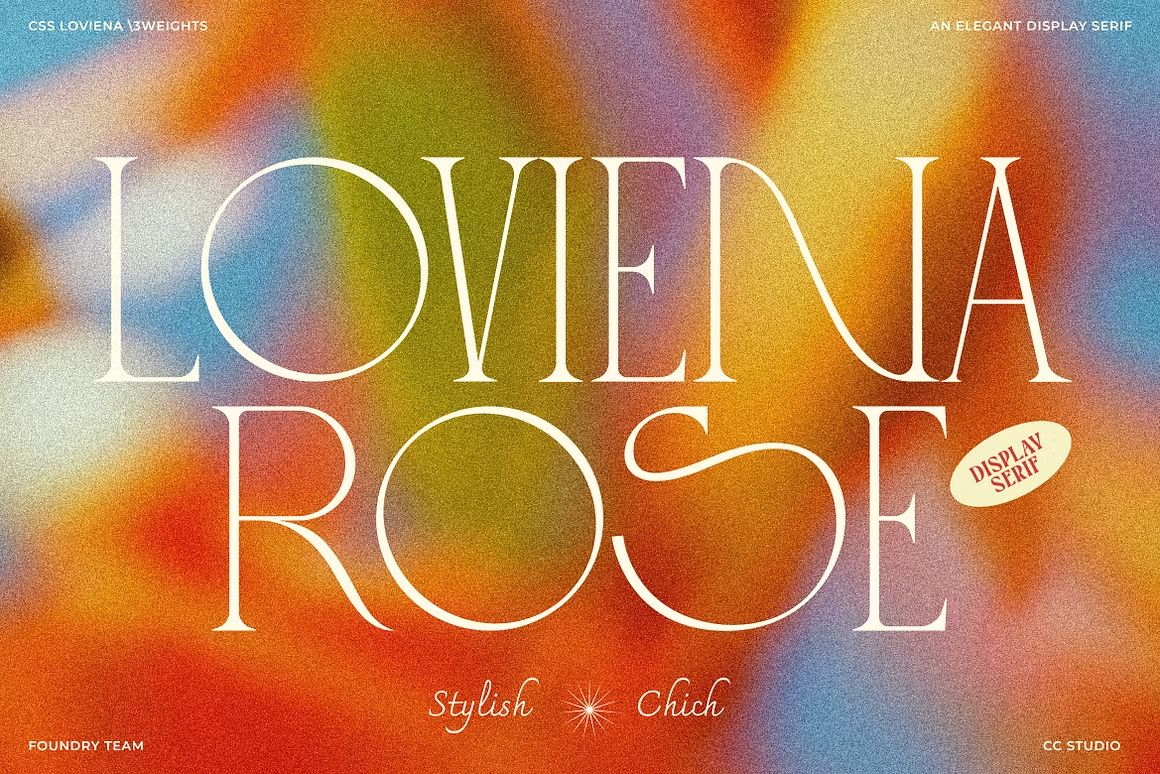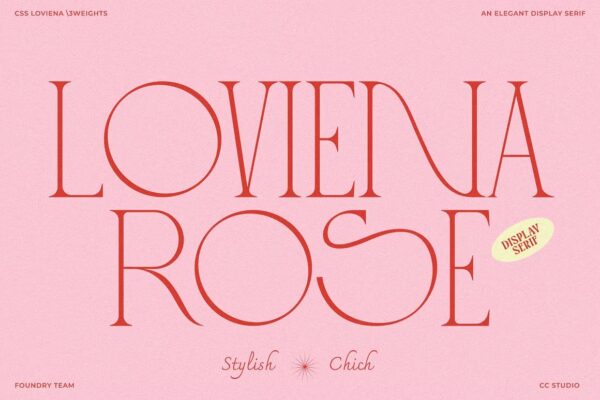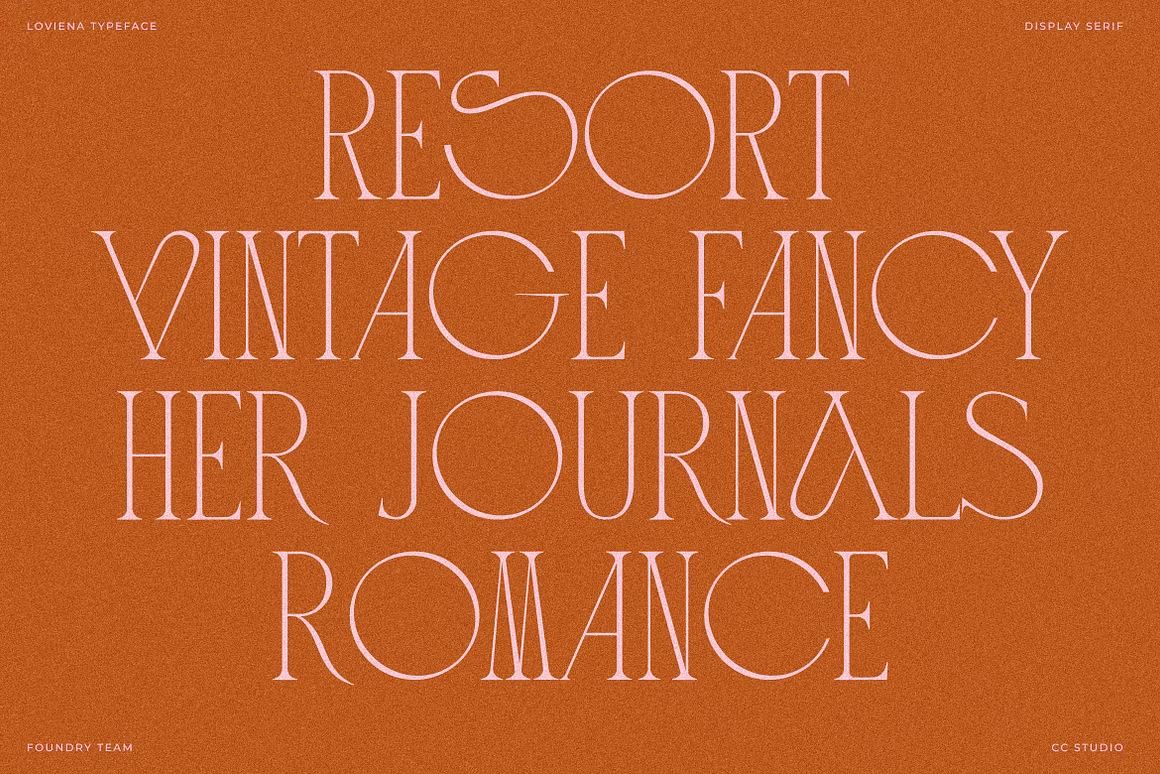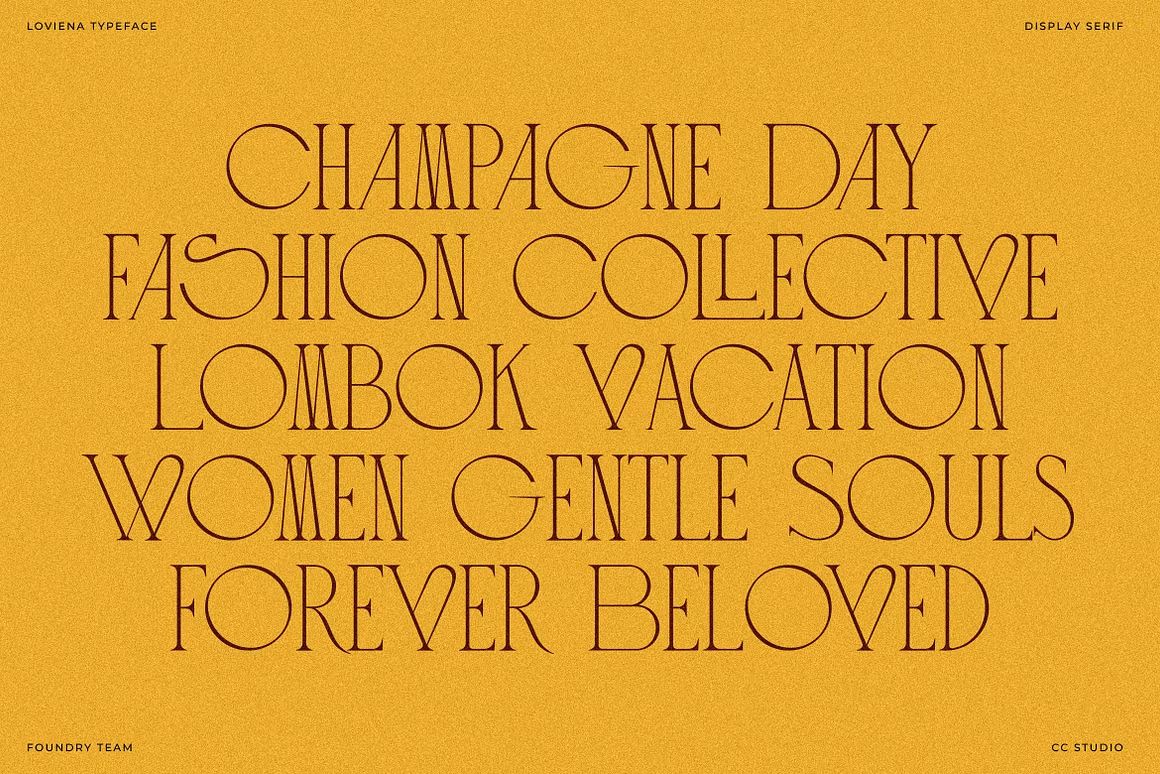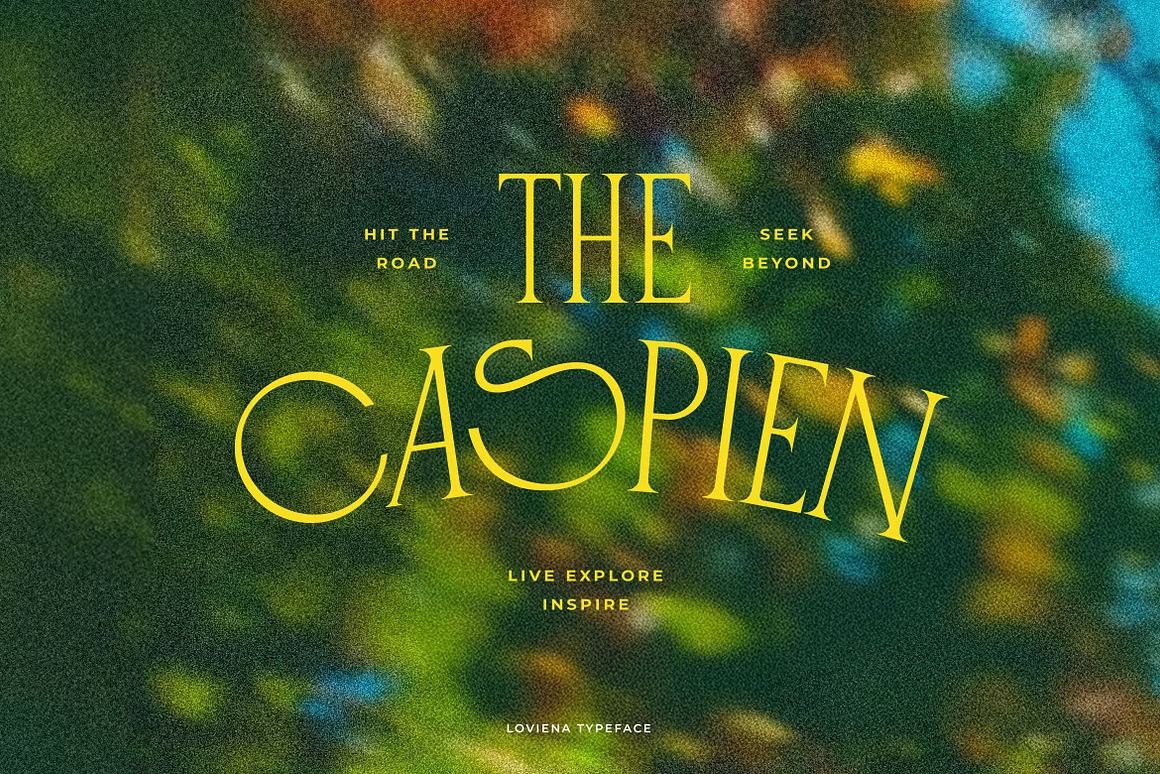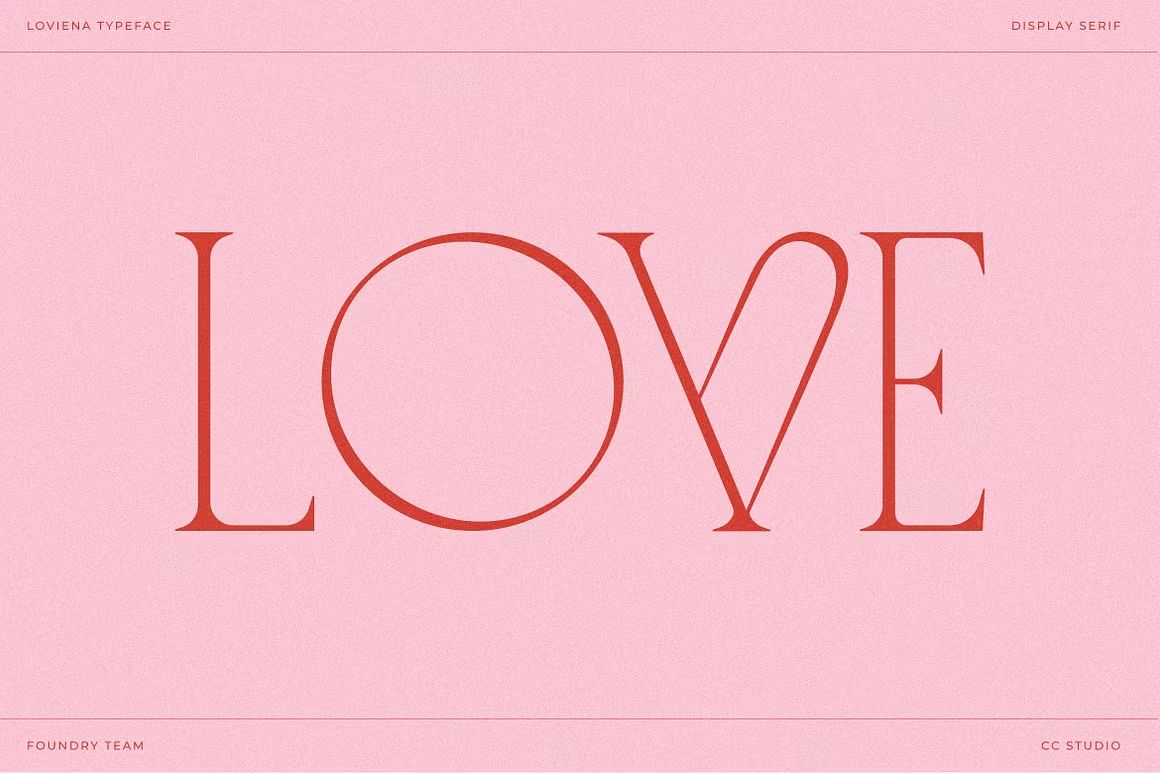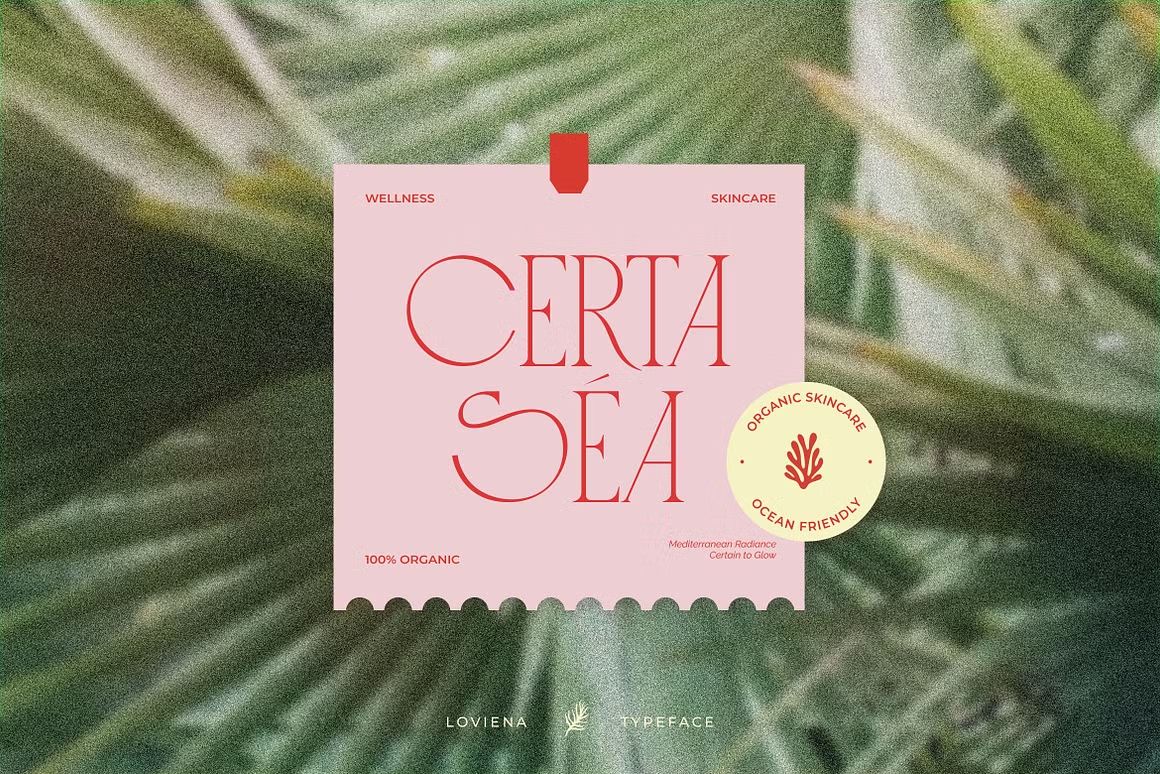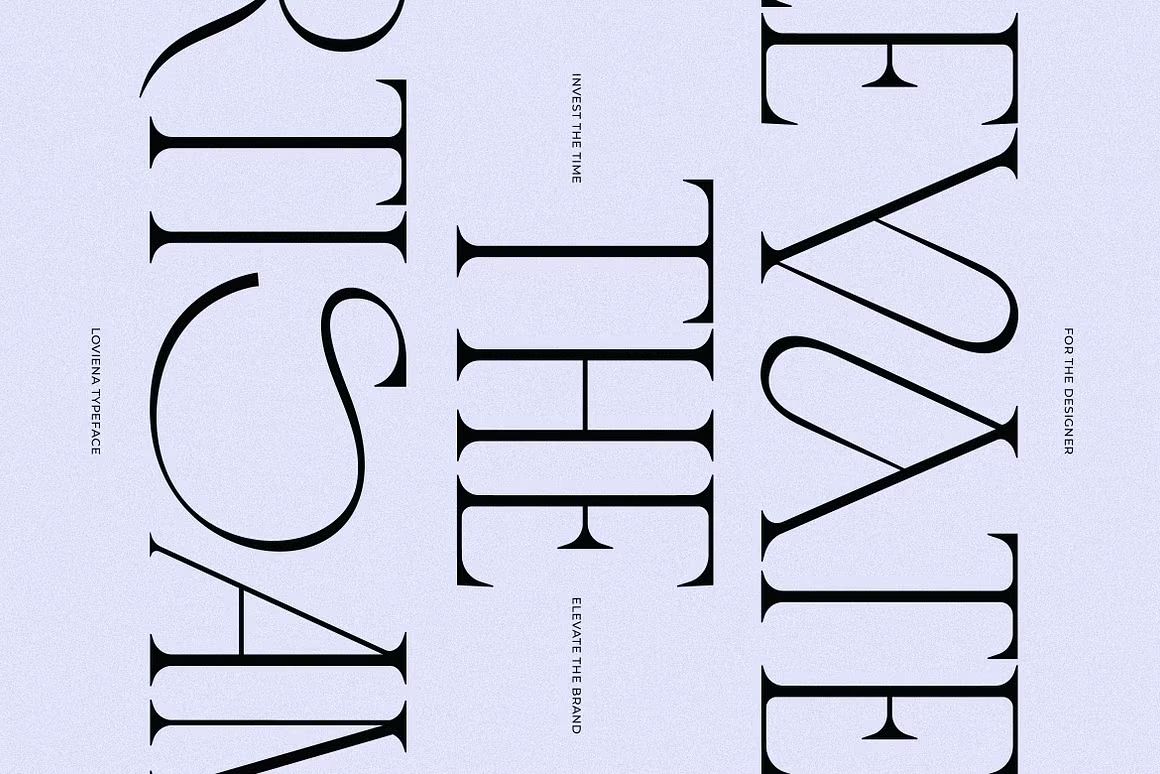
Loviena Rose – Sans Serif Font
Loviena Rose adalah font sans serif elegan bergaya modern dan feminin. Cocok untuk branding, fashion, dan desain minimalis. Format OTF/TTF/WOFF, siap digunakan.
Loviena Rose adalah font sans serif bergaya modern dengan sentuhan feminin dan elegan. Karakternya ramping, bersih, dan halus, menjadikannya sempurna untuk branding, kemasan produk kecantikan, editorial fashion, logo minimalis, dan desain media sosial. Dengan keseimbangan antara kesederhanaan dan keanggunan, Loviena Rose memberi kesan profesional sekaligus lembut.
• Sans serif modern dengan nuansa elegan dan feminin
• Ideal untuk branding fashion, kosmetik, dan desain editorial
• Termasuk huruf besar, kecil, angka, simbol, dan ligatur